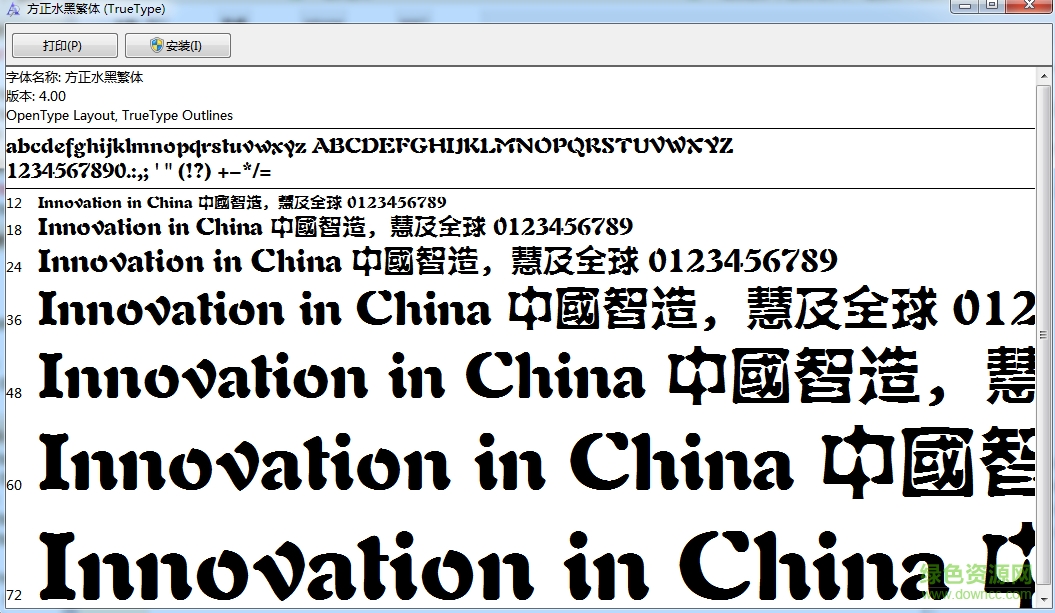
fzshhfw gb1 0
fzshhfw gb1 0字體是一款非常時(shí)尚的字體哦,這款字體是方正字體中的一款,也叫方正水黑繁體哦,有需要的朋友就來(lái)綠色資源網(wǎng)下載體驗(yàn)吧!
fzshhfw gb1 0字體介紹
fzshhfw字體就是方正水黑繁字體,字形粗狂而又工整,水滴效果漂亮。該字體適用領(lǐng)域十分廣泛,現(xiàn)綠色資源網(wǎng)提供fzshhfwgb10字體下載,有需要的就來(lái)吧!